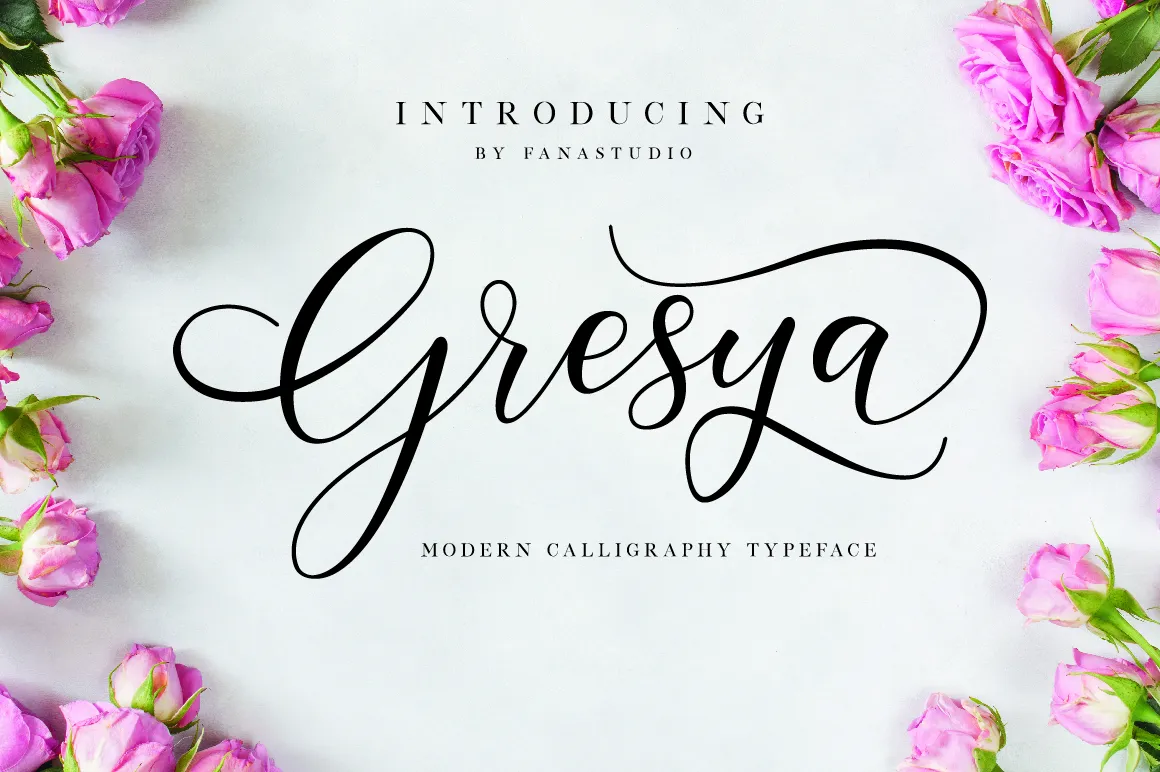
Descubra a sofisticação moderna que Gresya Script Font pode trazer para seus projetos de arte. Introduzida por Hamilton, esta elegante fonte script está feita para aqueles buscando uma mão na obra perfeita para dar vida à sua criatividade. Em um mundo onde o design pode transformar a sensação do seu trabalho, é crucial escolher bem. O Gresya é ideal para quem quer dar um toque pessoal a projetos artísticos sem abrir mão da qualidade. Seja você um designer de gráficos ou alguém que busca imprimir uma personalidade única em suas criações digitais, o Gresya pode ser sua fonte perfeita. Ele oferece ao seu projeto um olhar elegante e moderno. Estamos ansiosos para saber como a Gresya irá transformar seus projetos!